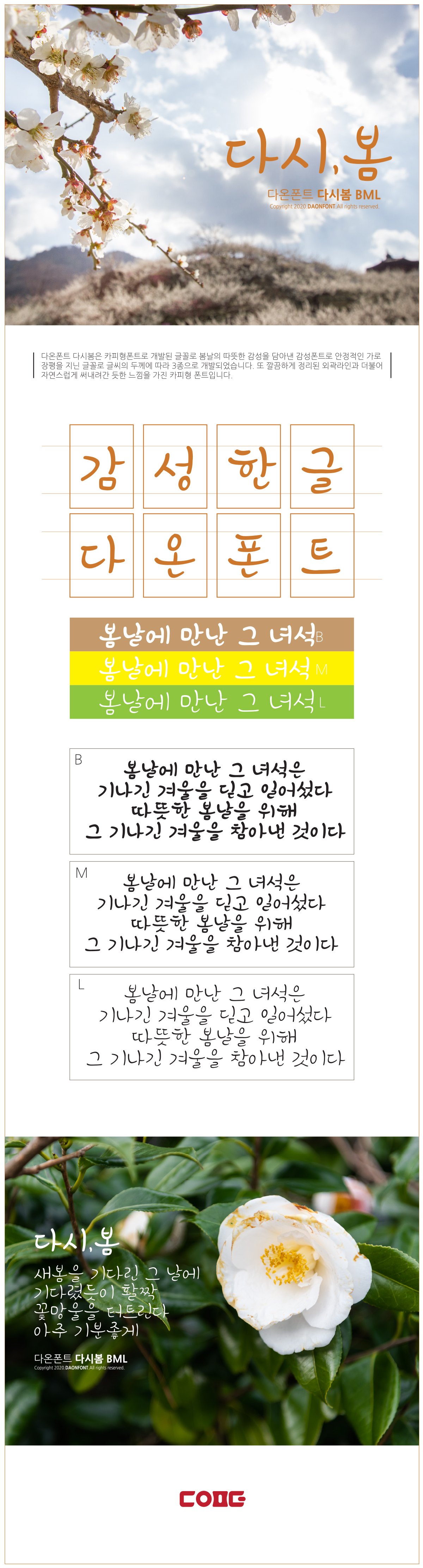
다온폰트 '다시봄'는 B, M, L 3가지 버전으로 출시 되었습니다.
폰트의 구성은 한글 2,350자의 한글과 영문, 숫자, 특수문자 일부로 구성된 폰트입니다.
다온폰트 '다시봄'은 카피형폰트로 개발된 글꼴로 봄날의 따듯한 감성을 담아내고
깔끔하게 정리된 외곽라인과 자연스럽게 써내려간 듯한 느낌을 가진 카피형폰트입니다.